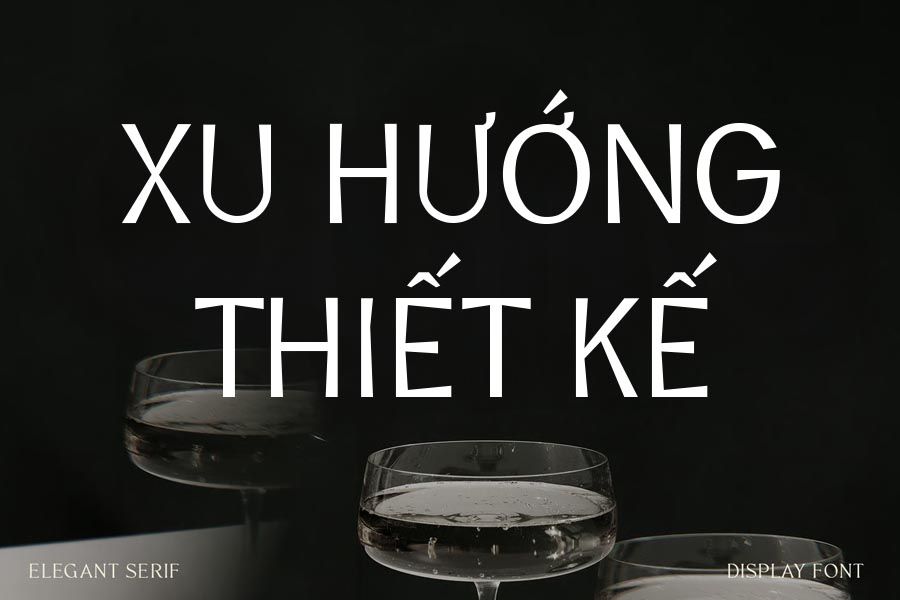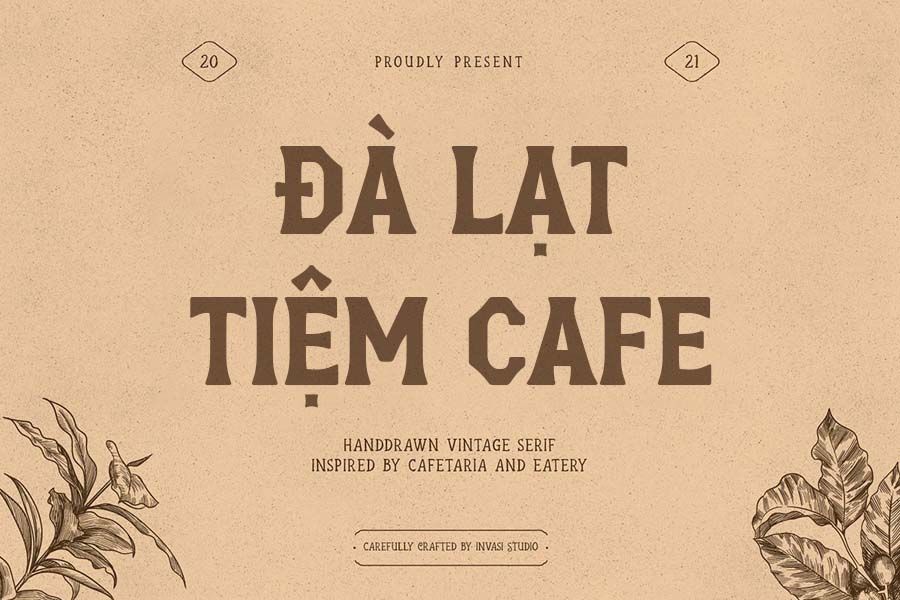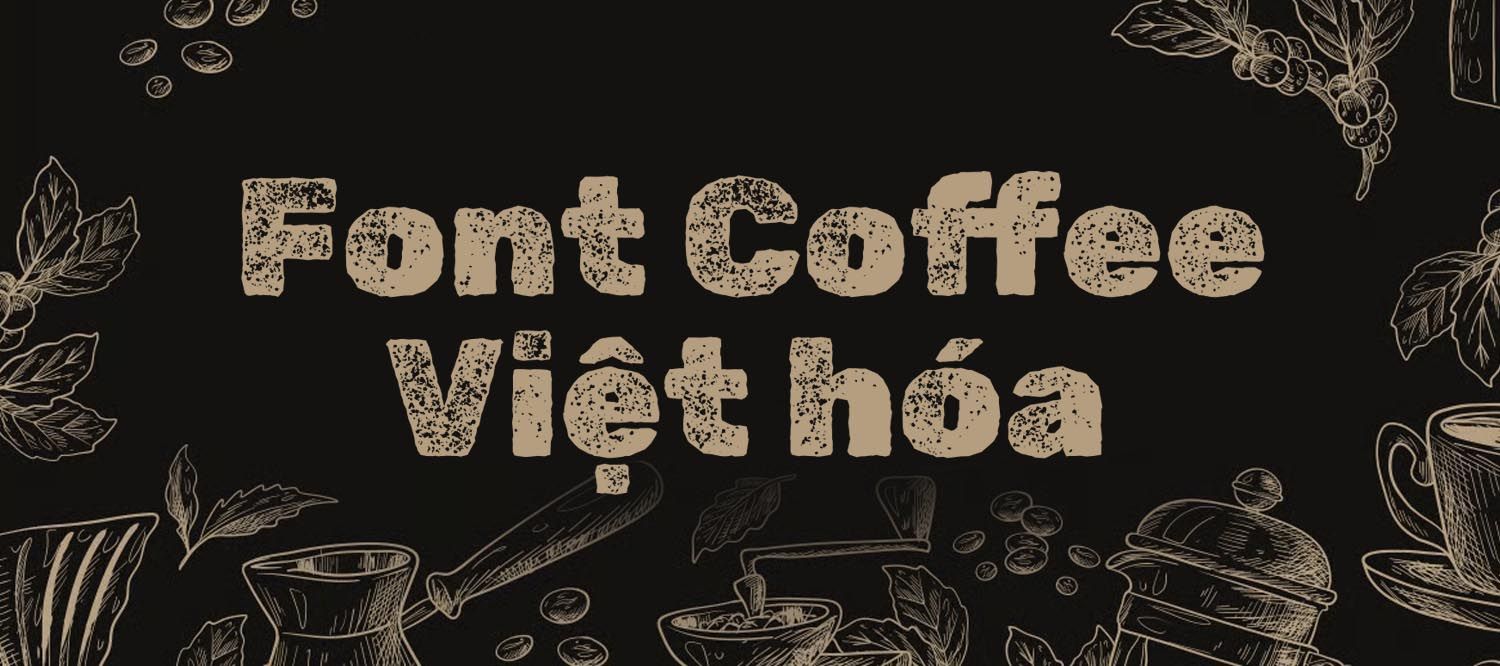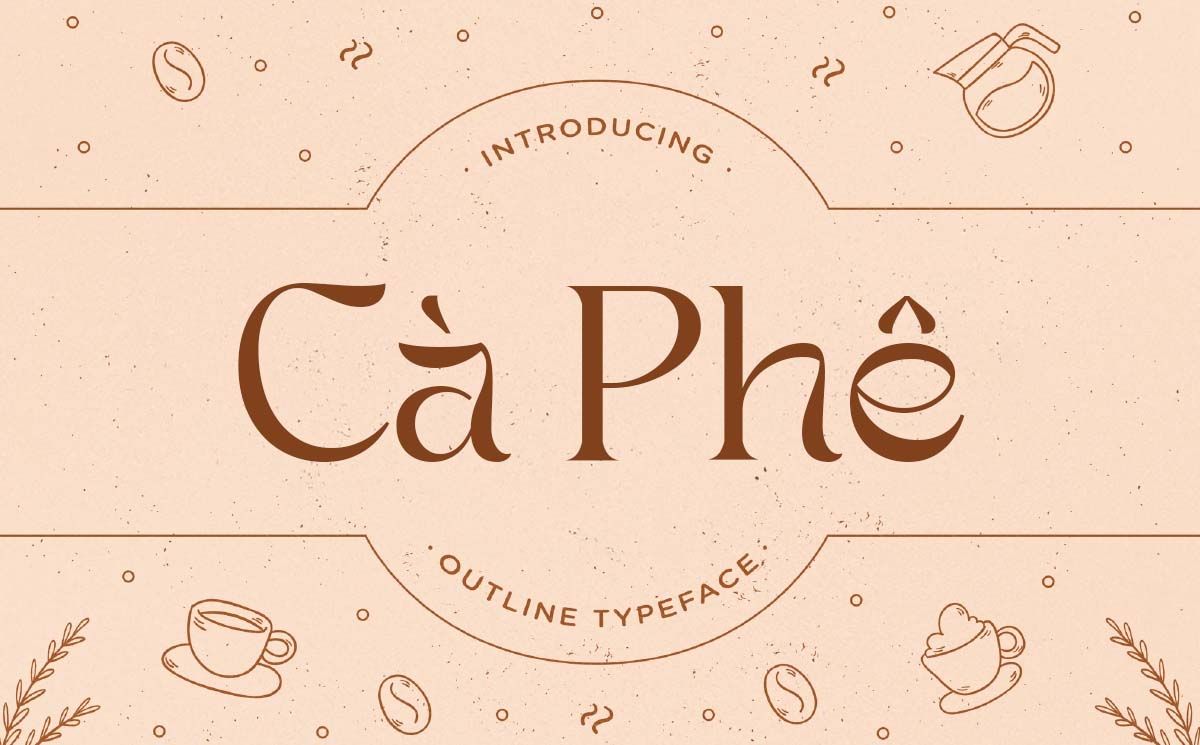
Tổng Hợp 10+ Font Coffee Việt Hóa Đẹp Cho Cửa Hàng Cafe
Giới thiệu về xu hướng font coffee
Trong ngành F&B (Food & Beverage), typography không chỉ là công cụ trình bày văn bản, mà còn là linh hồn của thương hiệu. Những font chữ mang hơi thở cà phê – thường gọi là font coffee – đang trở thành xu hướng nổi bật trong thiết kế nhà hàng, quán cà phê và thương hiệu đồ uống tại Việt Nam.
Nếu bạn đang xây dựng một thương hiệu F&B, việc lựa chọn font coffee Việt hóa sẽ giúp menu, logo, bao bì và poster quảng cáo trở nên gần gũi, ấm áp và dễ ghi nhớ hơn. Đặc biệt, với phiên bản Việt hóa đầy đủ dấu tiếng Việt, các font coffee không chỉ đẹp mắt mà còn dễ dàng ứng dụng vào thiết kế thương hiệu.
Font coffee Việt hóa là gì?
Font coffee Việt hóa là những kiểu chữ lấy cảm hứng từ cà phê, thường mang phong cách ấm áp, gần gũi, có thể là script mềm mại, retro hoài cổ hay hiện đại tối giản. Các font này được Việt hóa để hỗ trợ đầy đủ dấu tiếng Việt, nhờ vậy dễ dàng áp dụng trong logo, menu, bao bì, poster cho quán cà phê, nhà hàng.
Khác với bản gốc vốn chỉ tối ưu cho tiếng Anh hoặc Latin, phiên bản Việt hóa giúp thương hiệu F&B vừa giữ trọn nét thẩm mỹ độc đáo, vừa đảm bảo sự chuyên nghiệp và dễ đọc cho khách hàng Việt.
Top 10+ Font Coffee Việt Hóa Đẹp Nhất 2025
Dưới đây là danh sách 10+ font coffee Việt hóa được tuyển chọn kỹ lưỡng, đảm bảo đẹp, ứng dụng cao, tải nhanh.
1. Font coffee Việt hóa SVN Bestagrach – Thanh lịch & Hiện đại
SVN Bestagrach mang hơi thở thanh lịch, tinh tế với những đường nét serif sang trọng. Font này thích hợp để thiết kế menu, poster hoặc logo quán cà phê – nhà hàng cao cấp, tạo cảm giác chuyên nghiệp và hiện đại. Đặc biệt, kiểu chữ có độ cân đối cao, dễ đọc và dễ ứng dụng trên nhiều chất liệu in ấn. Đây là lựa chọn hoàn hảo để định hình phong cách thương hiệu ẩm thực sang trọng.
2. Font coffee Việt hóa TH Morucas – Cổ điển & Vintage
TH Morucas sở hữu phong cách vintage cổ điển, với những đường nét mềm mại nhưng vẫn giữ độ chắc chắn cần thiết. Font này rất phù hợp để dùng trong thiết kế bảng hiệu, menu hoặc poster quảng cáo cho quán cà phê mang phong cách hoài niệm. Sự kết hợp giữa cổ điển và tính ứng dụng hiện đại giúp TH Morucas trở thành font coffee Việt hóa lý tưởng cho các nhà hàng phong cách retro.
3. Font coffee Việt hóa SVN Rubik Dirt – Vintage & Cá Tính
SVN Rubik Dirt mang phong cách vintage bụi bặm, mạnh mẽ. Với hiệu ứng “dirty” độc đáo, font này rất hợp cho poster quán cà phê, thiết kế bảng hiệu hoặc menu phong cách retro. Phiên bản Việt hóa hỗ trợ đầy đủ dấu tiếng Việt, giúp dễ dàng ứng dụng mà không mất đi nét cá tính đặc trưng.
4. Font coffee Việt hóa SVN Moshimoshi – Tết & Hoài Cổ
SVN Moshimoshi là font mang phong cách lễ hội, hoài cổ với nét chữ độc đáo, rất thích hợp cho thiết kế menu dịp Tết, poster quảng bá hay bao bì sản phẩm quán cà phê truyền thống. Với sự kết hợp hài hòa giữa cổ điển và vui tươi, font này giúp tạo nên không khí ấm áp, gần gũi cho thương hiệu F&B.
5. Font coffee Việt hóa SVN Heritage – Retro & Nghệ Thuật
SVN Heritage mang nét retro hoài cổ, đường nét vững chắc, dễ đọc. Font này phù hợp cho logo quán cà phê phong cách cổ điển, menu vintage và poster quảng bá nghệ thuật. Bản Việt hóa giữ trọn phong cách retro nhưng thêm sự tiện lợi khi dùng trong tiếng Việt. Đây là lựa chọn tuyệt vời cho các thương hiệu muốn nhấn mạnh tính nghệ thuật và cá tính riêng.
Tác giả gốc: Vintage Voyage Design
Việt hóa: Team SVN
📁
Tải SVN Heritage
6. Font coffee Việt hóa TH Buttian Regular – Nghiêng Mềm Mại
TH Buttian Regular là một font chữ nghiêng thanh thoát, mang lại sự mềm mại và tinh tế. Đây là kiểu chữ rất hợp cho menu quán cafe, bao bì sản phẩm hoặc thiệp mời với phong cách trang nhã. Nhờ đường nét uyển chuyển nhưng dễ đọc, TH Buttian Regular mang đến trải nghiệm thẩm mỹ vừa gần gũi vừa sang trọng.
Tác giả gốc: Creatype Studio
Việt hóa: Team TH
📁
Tải TH Buttian Regular
7. Font coffee Việt hóa TH Flarida – Viết Tay Uyển Chuyển
TH Flarida là font chữ viết tay mềm mại, với những nét uốn lượn tinh tế. Font này thích hợp để thiết kế bao bì sản phẩm, logo quán cà phê, hoặc poster quảng bá cần sự nữ tính và gần gũi. Với phiên bản Việt hóa chuẩn, TH Flarida hỗ trợ đầy đủ dấu tiếng Việt, giúp bạn dễ dàng ứng dụng cho mọi thiết kế ẩm thực – F&B.
Tác giả gốc: Letterhend Studio
Việt hóa: Team TH
📁
Tải TH Flarida
8. Font coffee Việt hóa TH Choco Chici – Hoạt Hình & Dễ Thương
TH Choco Chici mang phong cách hoạt hình vui nhộn, với những đường nét tròn trịa, đáng yêu. Đây là font coffee Việt hóa rất thích hợp cho menu quán cà phê trẻ trung, trà sữa hoặc tiệm bánh ngọt. Với sự vui tươi và mềm mại, font này giúp thương hiệu trở nên gần gũi, dễ tiếp cận hơn với giới trẻ và gia đình.
Tác giả gốc: Letterhend Studio
Việt hóa: Team TH
📁
Tải TH Choco Chici
9. Font coffee Việt hóa TH Erva Esra – Thanh Lịch & Cổ Điển
TH Erva Esra mang phong cách serif cổ điển, với các đường nét tinh xảo và đầy tính thẩm mỹ. Đây là font cực kỳ phù hợp cho thiết kế logo nhà hàng, menu cao cấp hoặc các ấn phẩm quảng cáo sang trọng. Sự kết hợp giữa nét cổ điển và sự cân đối trong từng chi tiết giúp Erva Esra dễ dàng trở thành điểm nhấn trong mọi thiết kế F&B.
Tác giả gốc: Creatype Studio
Việt hóa: Team TH
📁
Tải TH Erva Esra
10. Font coffee Việt hóa TH Cungcap 13 – Thể Thao & Vintage
TH Cungcap 13 sở hữu phong cách thể thao mạnh mẽ pha chút vintage hoài cổ, rất phù hợp cho menu quán cà phê cá tính, poster sự kiện hoặc logo thương hiệu năng động. Với sự cân đối trong từng chi tiết, font coffee Việt hóa này tạo nên điểm nhấn độc đáo, vừa khỏe khoắn vừa gợi cảm giác retro.
Tác giả gốc: BL Fonts
Việt hóa: Team TH
📁
Tải TH Cungcap 13
Hướng dẫn tải & cài đặt font coffee Việt hóa
1. Tải font từ nguồn uy tín (S99.vn, Fontdep.vn).
2. Giải nén file .zip → copy vào thư mục Fonts.
3. Với Mac: double-click → Install Font.
4. Mở Photoshop/Illustrator/Canva và bắt đầu sử dụng.
Câu hỏi thường gặp (FAQ)
Font coffee Việt hóa có miễn phí không?
Có, nhiều font coffee Việt hóa được cung cấp miễn phí trên
S99.vn, bên cạnh các bản premium cao cấp.
Tôi có thể dùng font coffee Việt hóa cho mục đích thương mại không?
Tùy font. Bạn nên kiểm tra thông tin bản quyền trên trang tải để đảm bảo an toàn khi dùng cho logo, menu hoặc bao bì.
Font coffee Việt hóa khác gì font chữ retro hay vintage?
Font coffee Việt hóa thường được thiết kế riêng cho ngành F&B, tạo cảm giác ấm áp, gần gũi hơn. Trong khi đó, font retro/vintage có phạm vi ứng dụng rộng hơn.
Nên chọn font coffee Việt hóa nào cho menu quán cà phê hiện đại?
Bạn có thể chọn SVN Bestagrach hoặc Kenyan Coffee Việt hóa – đều mang phong cách rõ ràng, sang trọng, dễ đọc.
Kết luận
Nếu bạn đang tìm font chữ để thiết kế menu, logo hoặc bao bì nhà hàng, bộ sưu tập 10+ font coffee Việt hóa trên sẽ là giải pháp hoàn hảo.